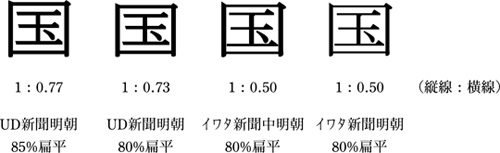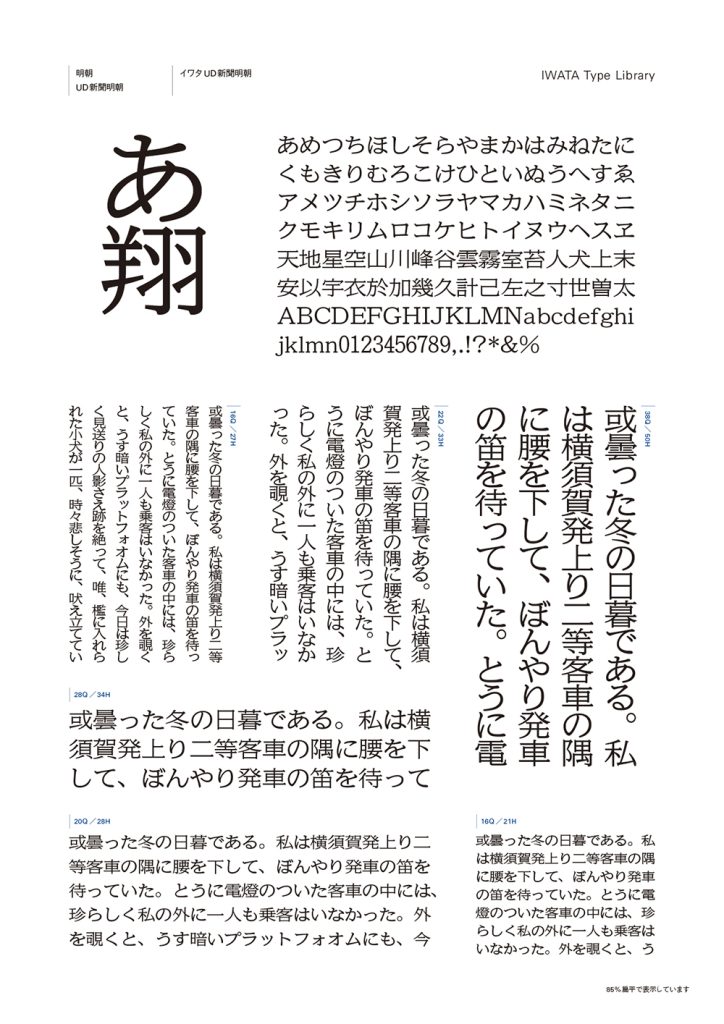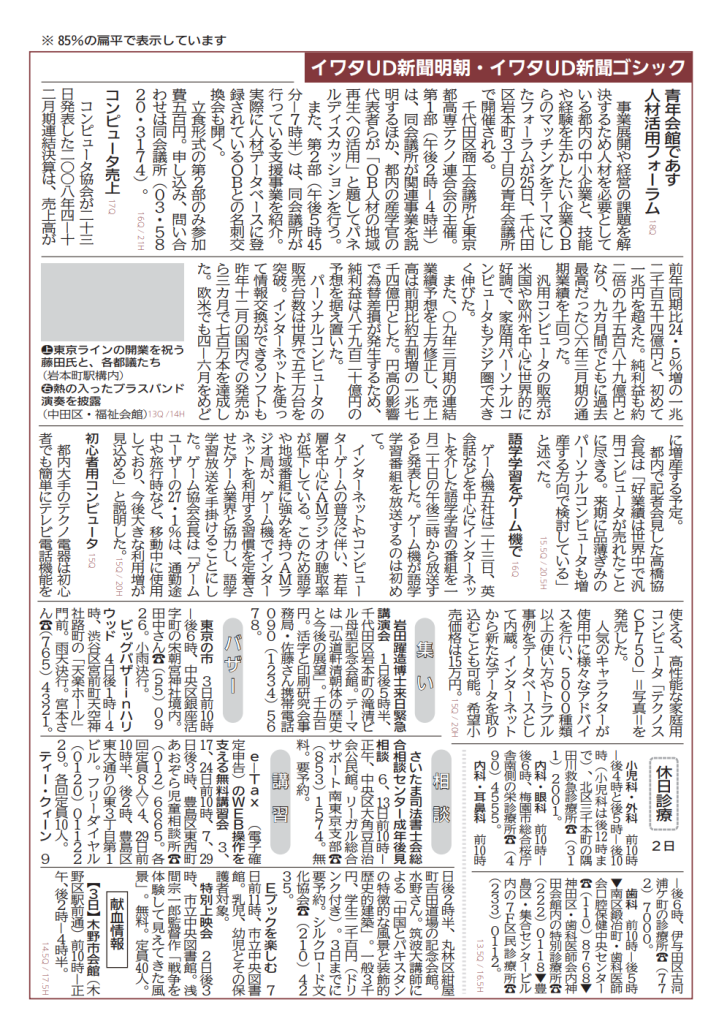
UD新聞明朝
イワタUD新聞明朝
情報量よりも読みやすさが求められる、時代の要請に対応した“次世代の新聞明朝体”です。信濃新聞社の協力により輪転機印刷テストを実施し、新聞印刷に最適化するように調整を施しています。視認性の良さと長文での読みやすさを兼ね備え、新聞本文だけでなく、情報を明瞭に伝えるあらゆる印刷物に適した書体です。
開発の背景
戦後間もない1951 年、新聞紙面では1 ページ15 段、1 段15 文字制がスタートしました。そして高齢化の進展に伴い、新聞紙面では大文字化のニーズが急速に高まったことで2008 年には多くの紙面の組み体裁が変更され、1 ページ15 段の枠から脱却し、12 段にして文字を大きくする新聞社も登場しました。しかし、本文サイズを単純に拡大するだけでは、読みやすく美しい紙面を実現することはできません。拡大された文字サイズにふさわしく、ユニバーサルデザイン(UD) の視点からも改良された新聞書体が求められるようになりました。このような環境の中で、イワタは誰にでも読みやすい新聞本文書体を開発するに至りました。
書体デザインのポイント
UDの思想に基づき、誰もが見やすく読みやすい文字であると同時に、文字の品位、平体での使用、広めのふところといった新聞書体の歴史的なプロポーションは引き継ぐなど、美しい紙面構成のための様々な工夫がされています。
※「イワタ新聞中明朝体」と「イワタUD 新聞明朝体」を比較しています(扁平率はどちらも85%)
新聞の読書環境において、一文字一文字が見やすいのは当然ですが、大量の縦組み文をスラスラ読めることが必須です。UD 新聞書体は文字が従来のものより縦長に見える、すなわち一行がかたまりとして見えることを意図したデザインです。